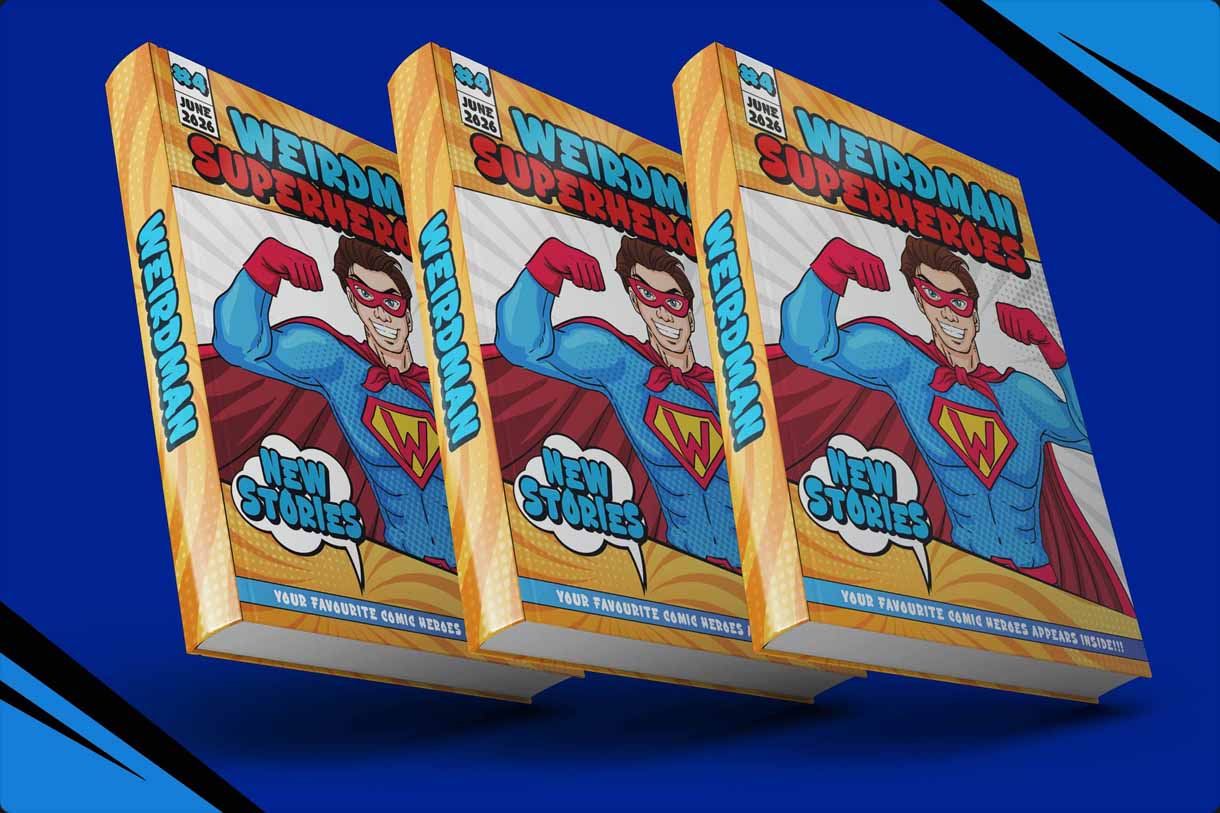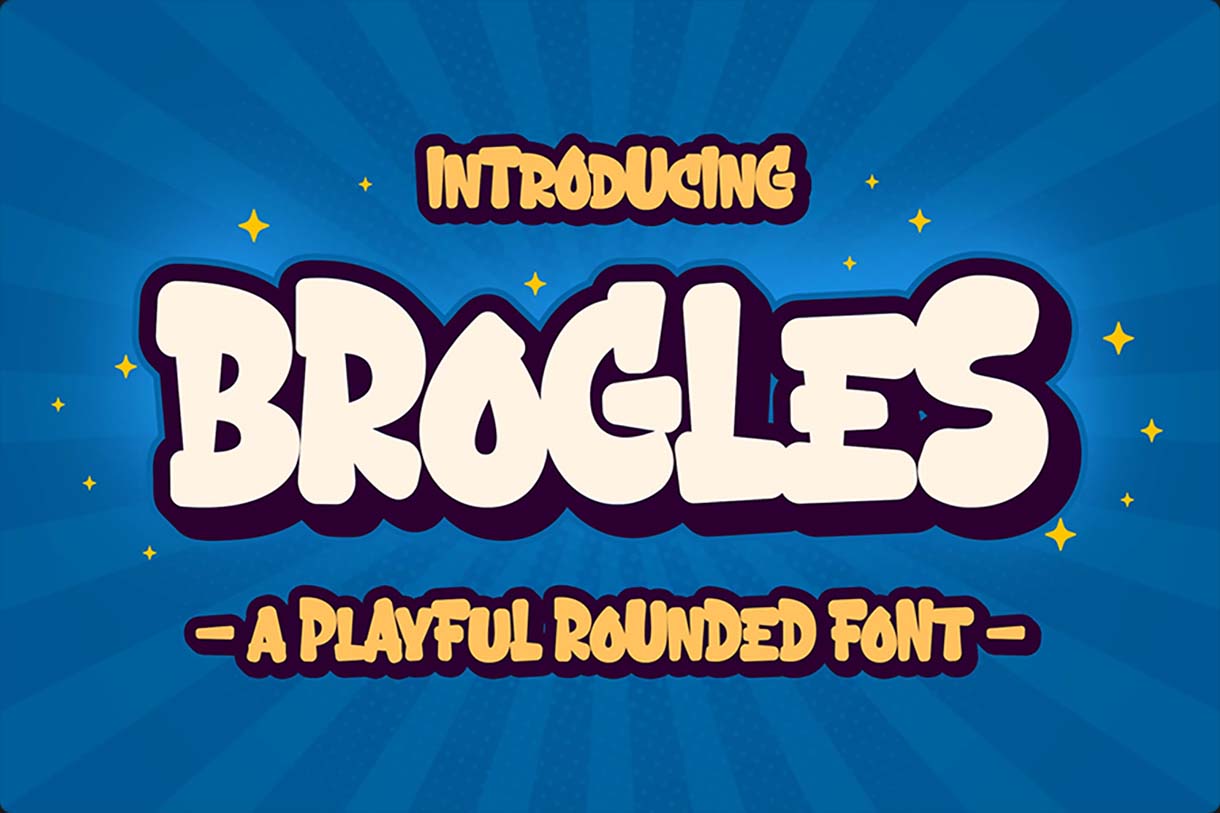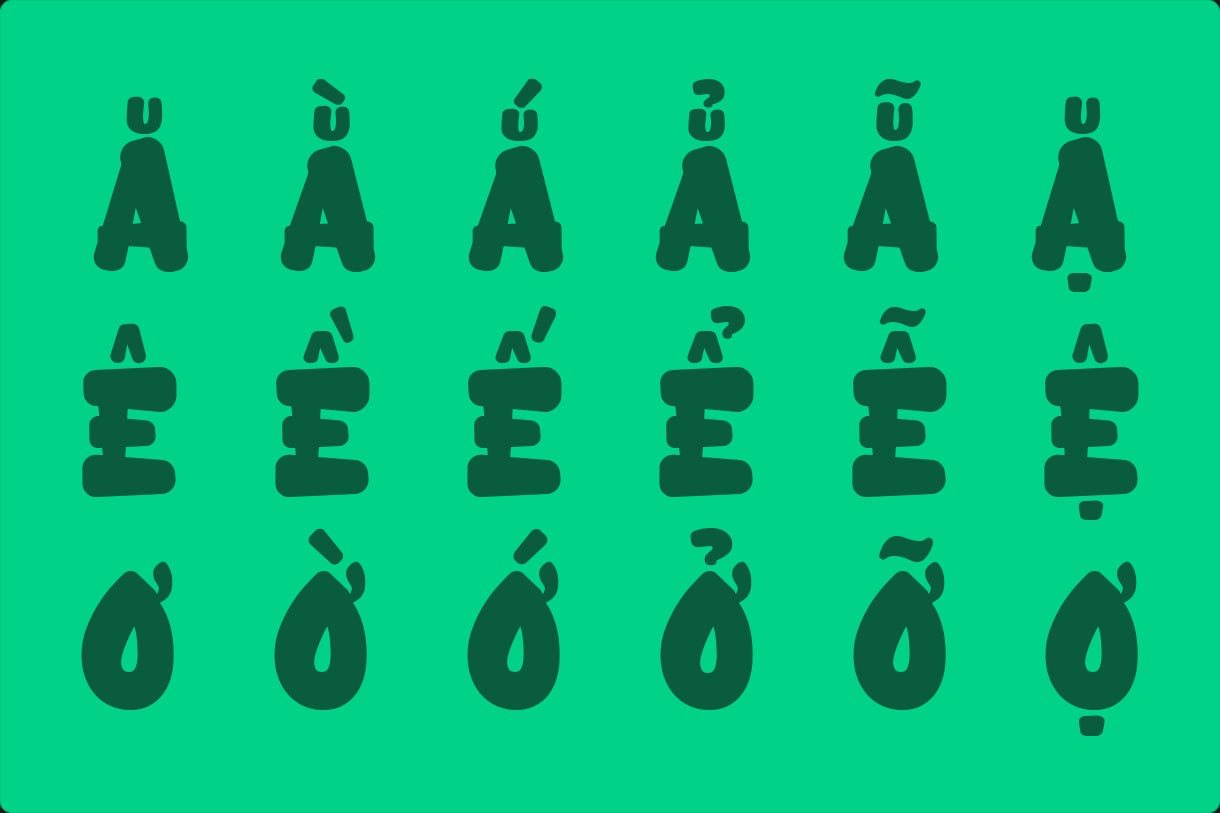
Fz Brogles – Font Chữ Hoạt Hình Việt Hóa Ngộ Nghĩnh, Sáng Tạo & Thân Thiện
Nếu bạn giống mình – thường xuyên thiết kế các ấn phẩm dành cho trẻ em, hoạt hình, hoặc những nội dung cần sự vui tươi, thì chắc hẳn cũng từng đau đầu đi tìm một font chữ vừa dễ thương, vừa hỗ trợ đầy đủ tiếng Việt. Trong một lần tình cờ lướt qua FontZin, mình phát hiện ra Fz Brogles, và sau khi dùng thử thì… thật sự thấy hài lòng!
1. Ấn tượng đầu tiên: dễ thương, đậm nét, rất “hoạt hình”
Font gốc của Fz Brogles là Brogles, do Bangkit Tri Setiadi thiết kế – cái tên khá quen thuộc với cộng đồng làm font quốc tế. Phiên bản Việt hóa được thực hiện bởi FontZin, và điều đầu tiên mình thấy là font này có nét bo tròn siêu dễ thương, chữ nào cũng dày dặn, nổi bật. Rất hợp cho tiêu đề, banner, poster, thiệp sinh nhật, sách ảnh thiếu nhi… nói chung là những thiết kế cần sự gần gũi và đáng yêu.
2. Font đã được Việt hóa hoàn chỉnh
Cái này là điểm cộng lớn nhất với mình. Font có đầy đủ dấu tiếng Việt, không bị lệch, không dính vào thân chữ – mình thử gõ mấy từ như “trẻ em”, “kỳ nghỉ”, “bánh kẹo”… thì thấy cực kỳ ổn. Mình làm luôn một vài poster cho trường mầm non và không cần căn chỉnh lại dấu gì hết.
3. Ứng dụng thực tế: rất đa năng trong thiết kế
Sau khi cài và test, mình đã dùng Fz Brogles cho:
• Bìa sách truyện tranh tự sáng tác
• Slide bài giảng cho giáo viên tiểu học
• Poster hoạt động ngoại khóa của các bé
• Thiệp sinh nhật + bao bì snack
• Logo tạm thời cho một kênh YouTube thiếu nhi
• Font này có thể phối cùng các icon, hình minh họa hoạt hình, background màu pastel là “auto dễ thương”. Cá nhân mình thấy rất hợp với các bạn làm trong ngành giáo dục, mầm non, hoặc các sản phẩm dành cho phụ huynh và trẻ nhỏ.
Mình đánh giá Fz Brogles là một font “ngon – bổ – dễ dùng” dành cho những ai đang làm thiết kế thiên về thiếu nhi, vui nhộn hoặc sản phẩm tiêu dùng trẻ em. Không cần phải cài thêm plugin hay lo căn chỉnh dấu, cứ gõ là ra nét đẹp rồi!